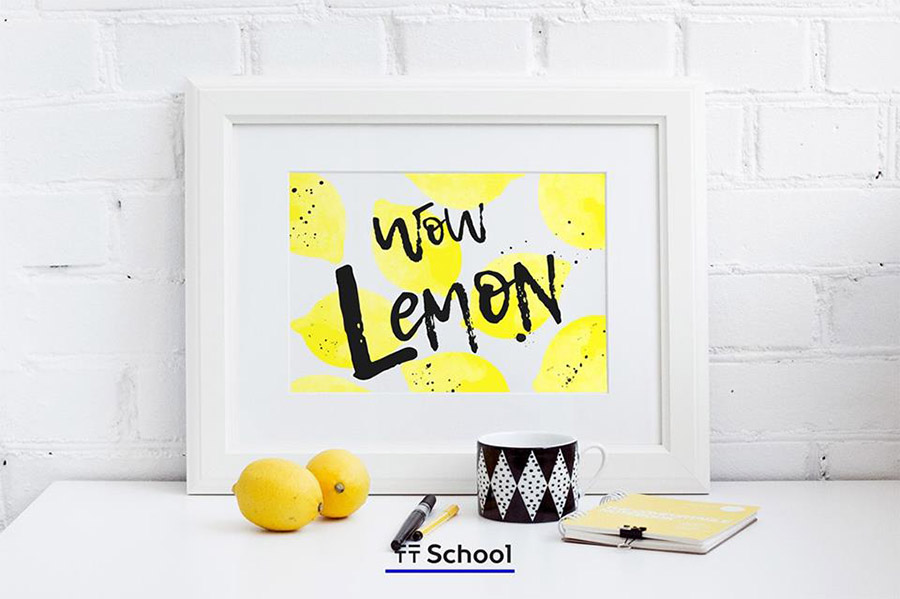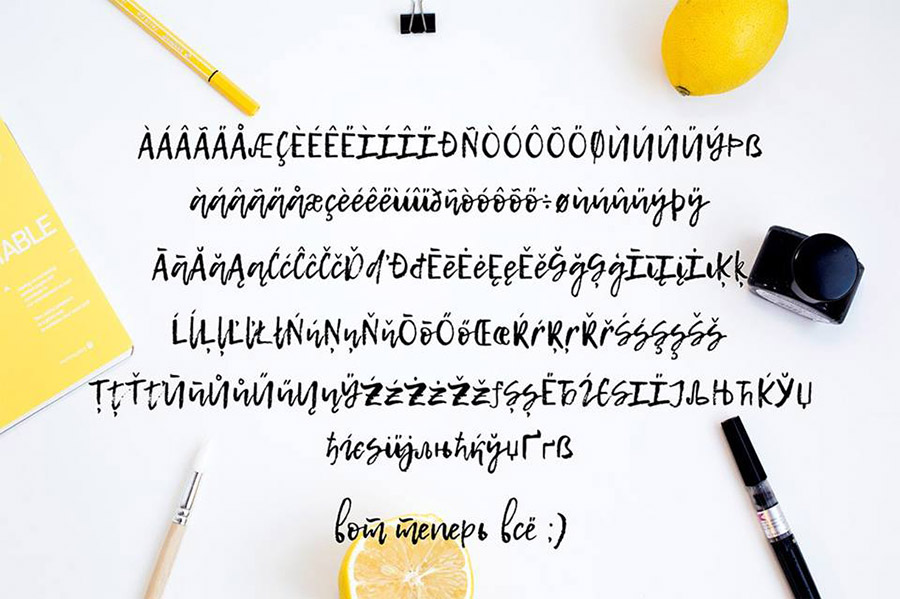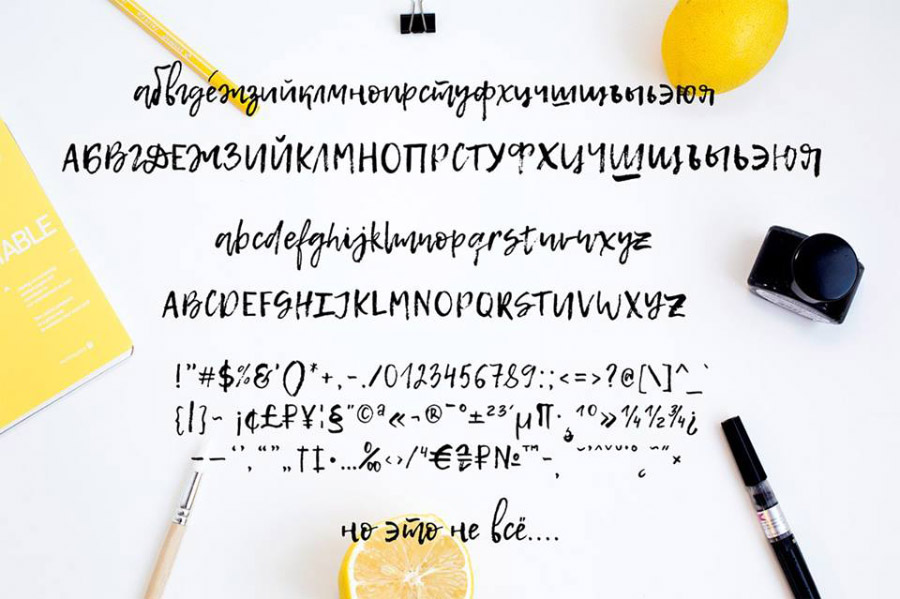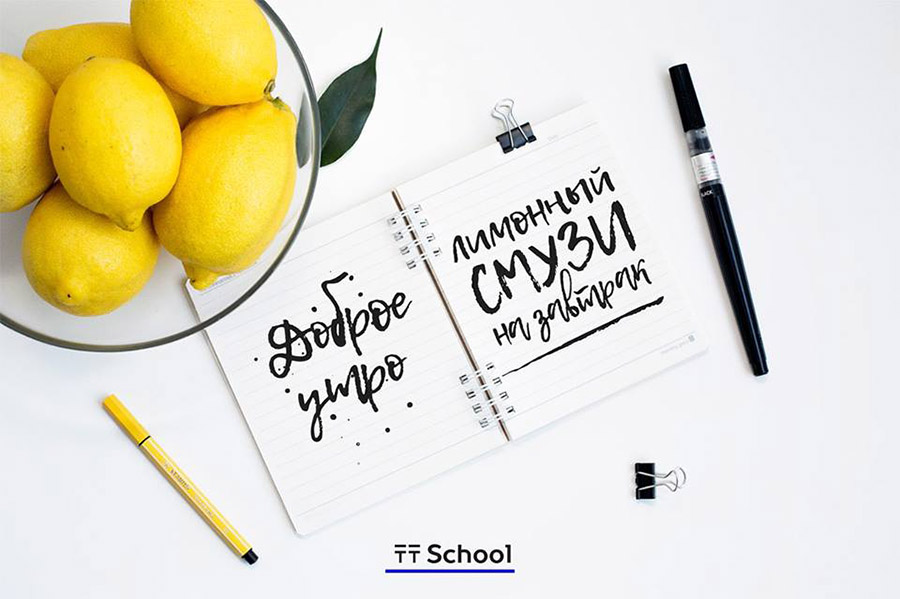
柠檬星期二手写的字体
这里的TypeType Foundry为您呈现新的免费超级意外字体,柠檬星期二手写字体。这种字体是基于表现力的作家书法 Daria Kwon 。这种字体在2016年8月由Typetypeschool在线课程“Your Font”中出现。柠檬星期二首先适用于短的情绪题词。因此,在社交网络和专业媒体上创造精美的内容将是巨大的。此外,该字体包含一组标准的西里尔文字符和一个扩展的拉丁语集合。